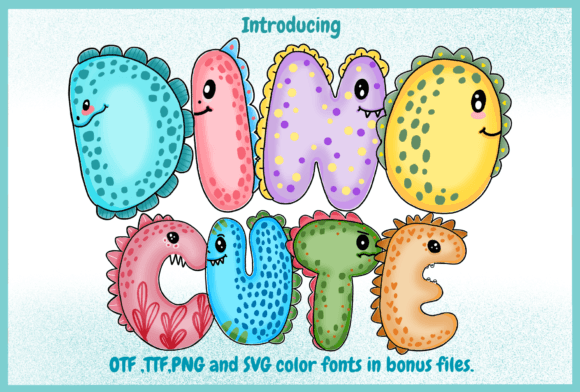
Dino Cute Font – خط دينو كيوت
أضف لمسة من المرح والجاذبية إلى تصميماتك مع Dino Cute Font! يتميز هذا الخط بأسلوبه اللطيف والمستوحى من عالم الديناصورات، مما يجعله مثاليًا لمشاريع الأطفال، العلامات التجارية المرحة، التصميمات الإبداعية، والمنتجات الرقمية.
???? مميزات الخط:
✅ تصميم فريد وممتع يجذب الانتباه
✅ مثالي للبوسترات، الشعارات، وتصميمات السوشيال ميديا
✅ يدعم الحروف الكبيرة والصغيرة لمرونة في الاستخدام
اجعل إبداعاتك تنبض بالحياة مع Dino Cute Font! ????✨